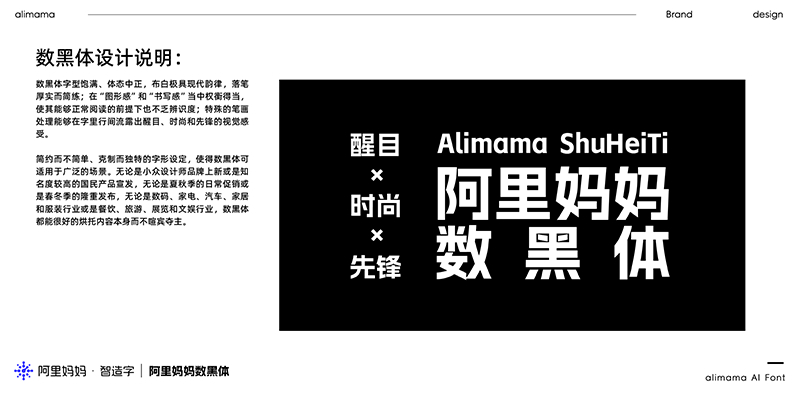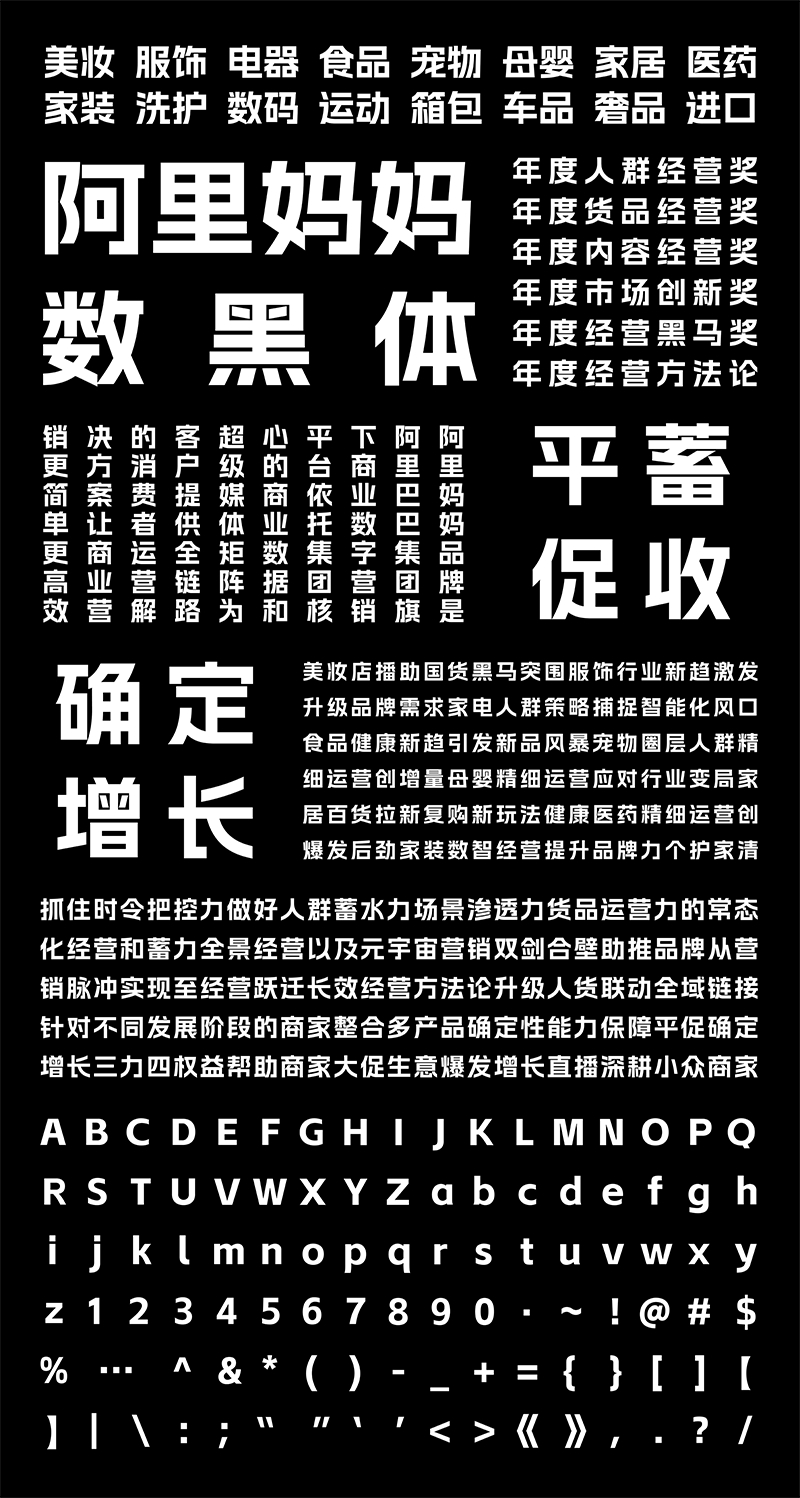
阿里媽媽·智造字自產自研打造了第一款AI字體產品——阿里媽媽數黑體正式上線。這款字的生成是人機協同工作的成果,設計原型,智能參與,人工干預,人機循環優化,直到最終生成滿意標準字庫。 數黑體是基於阿里媽媽營銷應用場景下產生的營銷字體,通用性和易用性強,適用於多品類商品,更高效的解決了電商類平臺的用字需求。
數黑體為中文簡體字庫,收納的中文字符包括但不限於GB2312,共計6767個漢字;英文大小寫共52個;常用標點符號共206個,總計7025個字符。 字型飽滿、體態中正,布白極具現代韻律,落筆厚實而簡練;字裡行間流露出先鋒、前衛和時尚的視覺感受。適用於電商、廣告、品牌形象、推廣物料等場景。